Download Font Terbaik untuk Desain Undangan Pernikahan Kekinian
Saya berupaya untuk selalu memperbaharui tulisan ini karena melihat adanya minat yang tinggi dari para desain grafis untuk mendapatkan hasil terbaik desain undangan yang dibuat. Baik undangan untuk pribadi atau untuk clien.
Pentingnya memilih font keren dalam mendesain undangan adalah hal yang tepat dilakukan. Jika anda memiliki desain yang elegan, maka pemilihan jenis script atau font kaligrafi akan terlihat menawan dalam undangan Anda.
Great Vibes, Sweet Sensation, Aphrodite Pro adalah beberapa contoh font dari sekian banyak lagi font lainnya yang sering digunakan desainer grafis dalam membuat undangan pernikahan.
Saat membuat desain undangan, entah itu undangan nikah, khitanan atau mungkin undangan ulang tahun, sering kali seorang desainer grafis kesulitan saat menentukan jenis huruf yang tepat untuk sebuah undangan.
Idealnya, untuk mendapatkan hasil dan contoh undangan yang baik, kesesuaian antara template desain undangan, ukuran, warna dan font harus benar-benar klop (cocok).
Nah, pemilihan font kerap menjadi salah satu masalah yang sering kali timbul.
Wajar sih, karena ada begitu banyak koleksi font yang bisa menjadi pilihan. Namun tentu tidak mungkin anda memilih satu persatu dari ribuan font yang ada.
Di sanalah letak kesulitannya.
Jika hal ini terjadi dengan anda sekarang, maka tidak perlu lagi khawatir. Karena saya akan membagikan font-font istimewa yang biasa digunakan desainer grafis di dunia dalam membuat kartu undangan.
Huruf-huruf cantik ini bisa anda gunakan dibagian cover undangan, isi/kata-kata undangan, atau seringnya dibagian nama kedua mempelai. Jadi tinggal disesuaikan dengan desain yang ada.
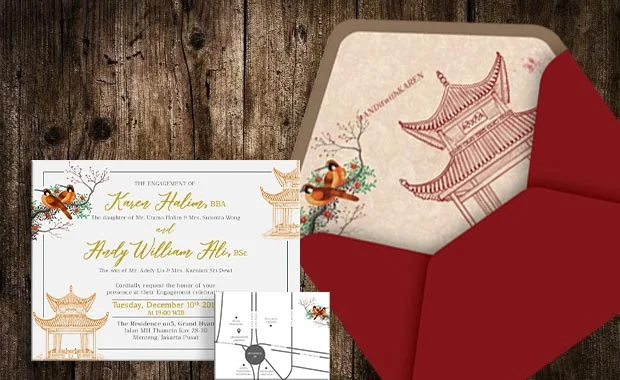
Rekomendasi Font Undangan Pernikahan Cantik dan Gratis!
1. Painter
Jenis font ini dibuat oleh Måns Grebäck dengan sangat baik dan sangat cocok digunakan untuk sebuah logo dan gambar lain pada desain undangan atau desain lainnya.
2. Alana You
Font ini terkesan menarik dan cantik. Akan lebih cocok jika font ini digunakan dalam desain undangan yang anda buat, terutama pada bagian nama mempelai.
Alana You Font dibuat Laura Worthington yang seorang desainer fonts dari Negara Bagian Washington.
3. Housegrind
Bukan hanya unik dan keren, font script ini memiliki daya tarik tersendiri. Apakah anda ingin mencoba merealisasikannya pada desain undangan pernikahan?
Font Housegrind ini dibuat oleh Måns Grebäck pada tahun 2013.
4. Sweet Sensations
Font jenis ini dibuat pada tahun 2016 oleh Billy Argel.
Anda bisa mencoba dan menggunakannya untuk mempercantik desain undangan pernikahan yang sedang anda buat.
Font Sweet Sensations ini terlihat sangat elegan dan mempunyai karakter tersendiri.
5. Birds of Paradise
Font ini adalah salah satu jenis huruf paling populer yang digunakan dalam kartu undangan pernikahan.
Birds of Paradise adalah font yang dikeluarkan oleh Herofonts, hasil karya dari Guilhem GRECO pada tahun 2014.
6. Mutlu Ornamental
Ini adalah font calligraphy unik yang bisa digunakan di berbagai media desain, termasuk desain pada undangan pernikahan.
Walau jenis huruf ini terkesan rumit pada penampakannya, namun font ini juga cukup populer dikalangan desainer grafis.
Mutlu Ornamental ini hasil karya dari Gazoz dengan kategori Calligraphy.
7. Great Vibes
Saya pikir anda cukup mengenal jenis font ini. Karena tentu saja font ini cukup familiar di kalangan desainer undangan.
Selain tampilannya yang cantik, font ini mempunyai kesan yang elegan dan cukup menarik untuk digunakan pada kartu undangan.
Great Vibes ini termasuk kategori font calligraphy dan script yang didesain oleh TypeSETit.
8. Variane Script
Variane Script adalah font script yang dirilis pada tahun 2015 oleh Work Ins Studio.
Font jenis ini memiliki sentuhan luar biasa yang sangat menarik jika dikombinasikan dengan ornamen, bunga atau pita pada kartu undangan pernikahan.
9. Mf Queen Leela
Gaya yang kontemporer pasti akan memberi tampilan kartu ucapan pernikahan anda cantik dan lebih menarik.